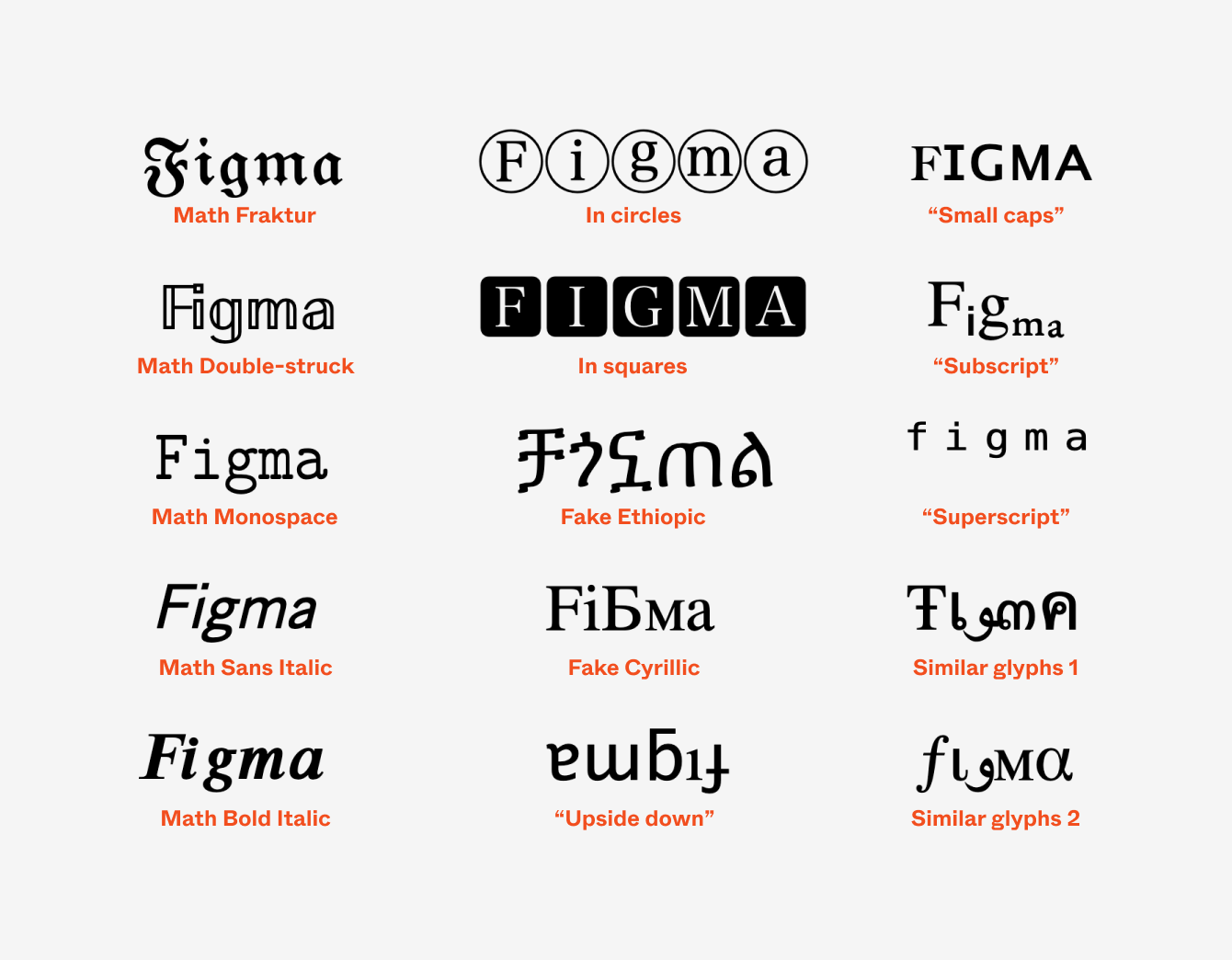
классификация шрифтов и основные понятия
Гармонично подобранный шрифт не только доносит информацию до аудитории, но и визуально дополняет проект. Ошибка в выборе шрифта может испортить впечатление и оттолкнуть зрителя от продукта, будь то афиша, вывеска магазина или кафе, упаковка товара, веб-сайт или приложение.
Интуитивно подбирать шрифты для проектов — мечта новичков и рядовая задача профессиональных дизайнеров. Чтобы из первой категории попасть во вторую, нужны годы тренировок и изучения типографики, насмотренность и теоретические знания о шрифтах.
Современная типографика предоставляет дизайнеру выбор из тысяч шрифтовых гарнитур. Рассказываем, как сориентироваться на первых этапах, чтобы найти подходящий шрифт.
Основные понятия типографики
Апертуры, засечки, начертания, стемы, арки, влития — от терминов, используемых в типографике, может закружиться голова. Особенно опасно погружаться в терминологию тем, кто только-только начинает знакомство со шрифтами.
Выдыхаем: многие из слов, используемых шрифтовыми дизайнерами, можно обойти стороной на первых шагах дизайна. Однако часть терминов полезно знать: так будет легче понять, на какие критерии смотреть при выборе шрифта.
Собрали мини-словарик терминов типографики.
- Шрифтовое семейство — набор разных шрифтов в одной гарнитуре. Шрифтовое семейство может включать разные шрифты по назначению, жирности и даже по стилю.
- Начертание — шрифт одной жирности. В шрифтовой гарнитуре может быть как 3 начертания, так и 9, от самого тонкого к самому жирному. Распространённые начертания: Thin, Regular, DemiBold, Bold.
- Засечки — это короткие дополнительные штрихи на конце основных элементов знака и перпендикулярные им.
- Кегль — так обозначают высоту символов шрифта, то есть размер по вертикали.
Какими бывают шрифты (классификация)
Единой классификации шрифтов, которой пользуются все дизайнеры, нет.
Можно разделять шрифты по историческим эпохам, в которые они появлялись, по визуальной форме, назначению.
Остановимся на типах шрифтов, знание которых точно пригодится в современной типографике.
По назначению можно выделить акцидентные и текстовые шрифты.
Акцидентные — шрифты, которые иногда называют заголовочными, так как ими оформляют заголовки или выделяют броские надписи. Это выразительные шрифты, которые приковывают взгляд зрителя.
Текстовые — шрифты для набора текста, могут называться наборными. Это шрифты с более спокойным характером, с высокой читаемостью даже в мелких текстах. Хороший текстовый шрифт не отвлекает от чтения, выглядит цельно и приятно.
Стилей шрифтов много, остановимся на самых распространённых: гротесках, антиквах и брусковых шрифтах.
Гротески — группа шрифтов без засечек. Это универсальные шрифты, функциональные и чаще спокойные по характеру.
Антиквы — группа шрифтов с засечками. Это шрифты чаще с классическим, элегантным или консервативным характером.
Брусковыми называют шрифты с брутальными, мощными засечками.
Многие шрифты не попадают в конкретную группу и находятся на стыке стилей.
Характеристики шрифтов
Назначение шрифта или стиль — далеко не всё. Каждый шрифт обладает своим характером.
Характерность шрифта — то, что выделяет гарнитуру среди остальных. Особые визуальные приметы, пропорции, графические особенности.
Студия TypeType, например, использует простые описания, которые помогают дизайнерам выбрать правильную сферу применения шрифта. Гарнитура может быть нейтральной по характеру, тогда сфера применения будет достаточно широкой, а может обладать выразительным характером: брутальным, технологичным, изящным.
Есть и другие характеристики, по которым шрифты могут отличаться: шириной, контрастом штрихов или букв, насыщенностью.
Широкий шрифт TT Norms® Pro Expanded относительно классического TT Norms® ProКонтраст — разница толщин между тонкими и жирными штрихами в знаках.
TT Marxiana — шрифт с высоким контрастомНачертание Regular менее насыщенное, чем начертание BlackКак определить хороший шрифт
Хороший шрифт — это гарнитура, подходящая проекту по характеру, ассоциациям и визуальному стилю. Любой шрифт может быть подходящий, если правильно его применять.
Плохих шрифтов не бывает, есть некачественные. С такими шрифтами сложно работать, так как набранный таким шрифтом текст не будет выглядеть гармонично, буквы могут наезжать друг на друга или, наоборот, быть слишком далеко. С подобными шрифтами невозможно работать, поэтому перед приобретением шрифта проверяйте его качество. Это можно сделать, скачав бесплатную версию, — такую возможность предоставляют многие студии.
Как подбирать шрифты
Сложно дать универсальную инструкцию по подбору шрифта, ведь дизайнеры тратят годы, чтобы научиться быстро выбирать необходимую гарнитуру.
Однако есть рекомендации, которые помогут выбрать подходящий шрифт.
1. Внимательно изучите характер шрифта, сравнивая его с позиционированием проекта. Например, если шрифт описан как «мягкий, плавный и воздушный», лучше выбрать его для компаний с таким же позиционированием, например, для бренда одежды, сшитой из натуральных тканей. Бренду в сфере IT такой шрифт вряд ли подойдёт, лучше подобрать что-то технологичное, а для банка или медицинской компании поискать более классический, традиционный шрифт со спокойным характером.